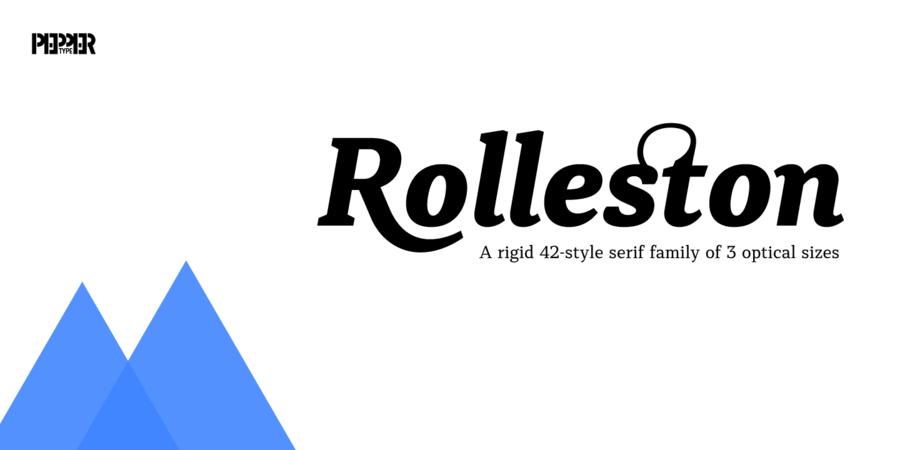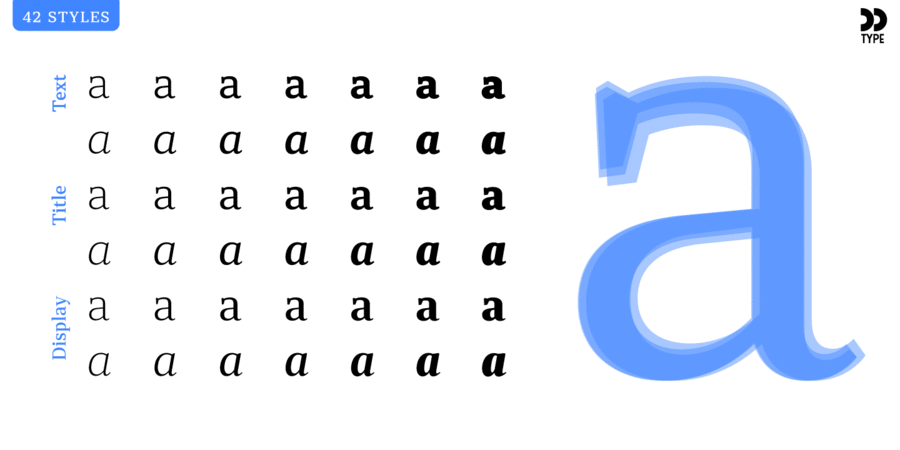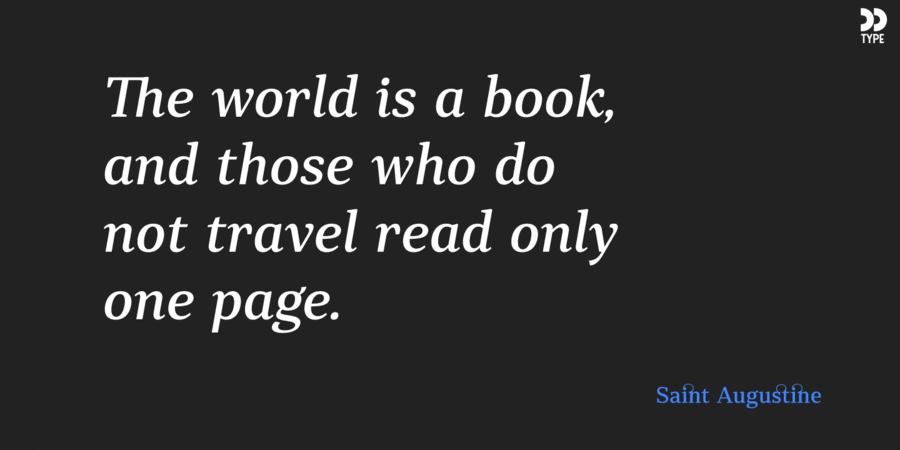
Rolleston Title – частина шрифтового сімейства Rolleston. Його 14 накреслень підходять для заголовків у книгах, журналах і на сайтах.
Rolleston – статичне шрифтове сімейство з клиноподібними зарубками. Гарнітура містить 42 накреслення, по 14 для трьох оптичних розмірів: Text, Title, та Display.
Ця гарнітура підтримує десятки мов на латиниці та кирилиці, містить різні опентайп-фічи, безліч лігатур і великий набір альтернативних гліфів. Це дозволяє створювати унікальні заголовки та красиві збалансовані тексти.
Шрифт розробив Олег Ліщук у 2018 році.
Асоціації з сімейством шрифтів Rolleston TitleОсобистість і характер гарнітури:
тонкий, легкий, делікатний, спокійний, рівний, гармонійний, врівноважений, космополітичний, технічний, сучасний, точний, логічний, статичний, культурний, освічений, серйозний, розумний, твердий, чіткий, різкий, худий, ввічливий, динамічний, витончений, елегантний, універсальний, зрозумілий, діловий, помірний, практичний, оптимальний, доступний, стійкий, формальний, ефектний, модний, якісний, елітний, дорогий, багатий, міський, добірний, благородний, красивий, майстерний, естетичний, виразний, пластичний, приємний, акуратний, гнучкий, стабільний, солідний, переконливий, мотивуючий, відповідальний, авторитетний, значний, суворий, міцний, важкий, щільний, помітний, яскравий, активний